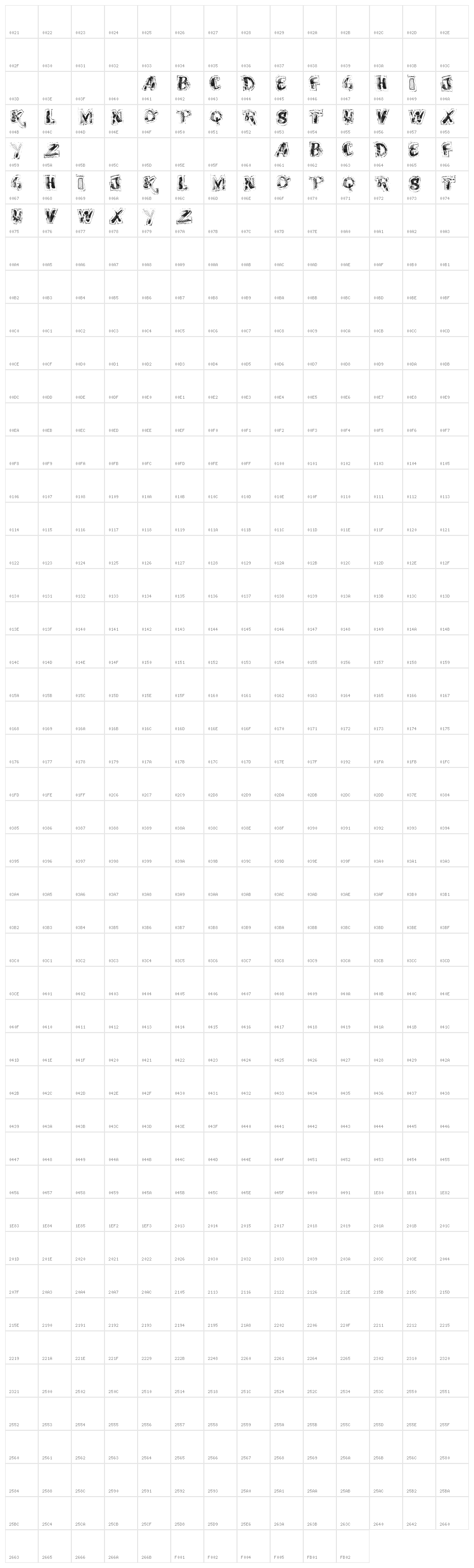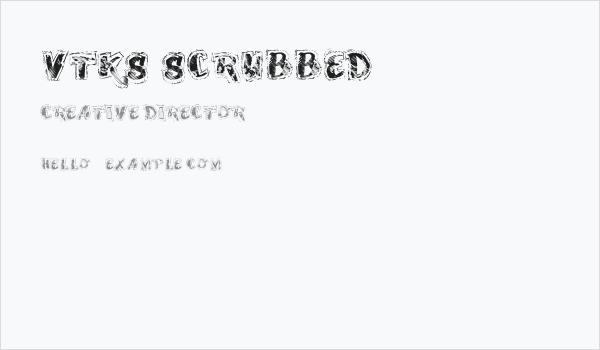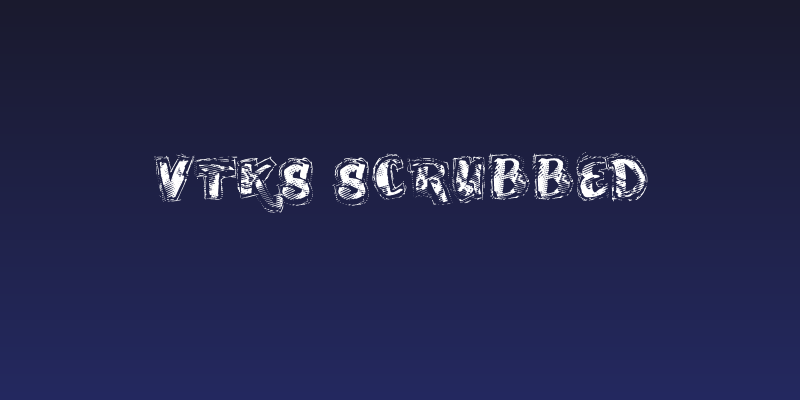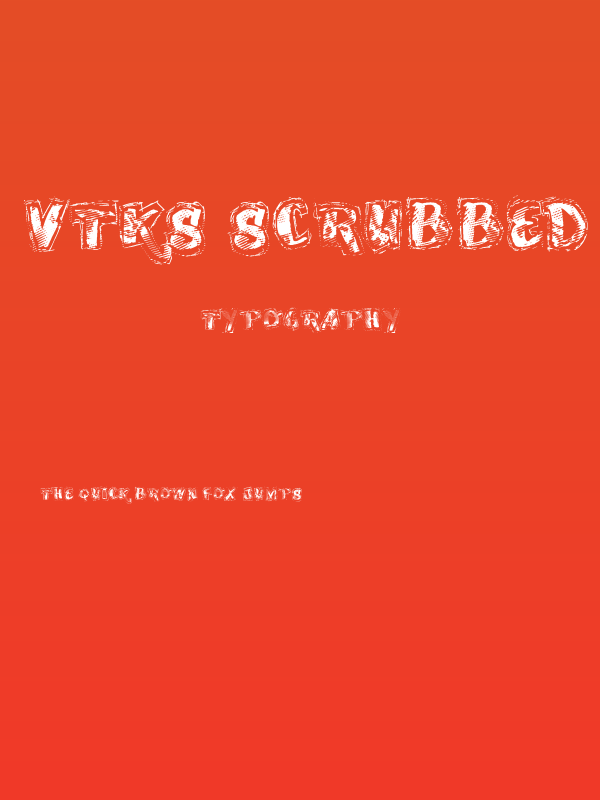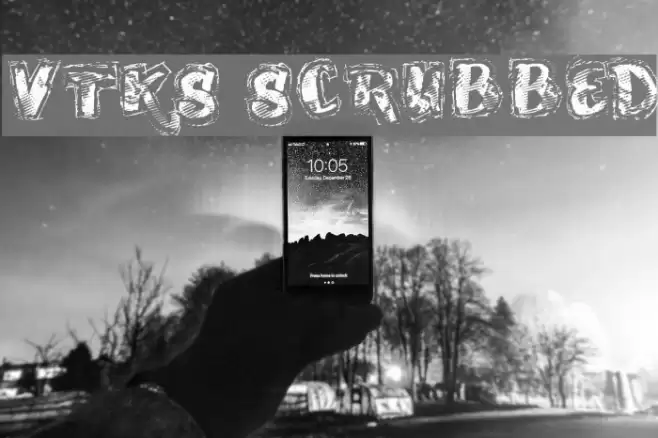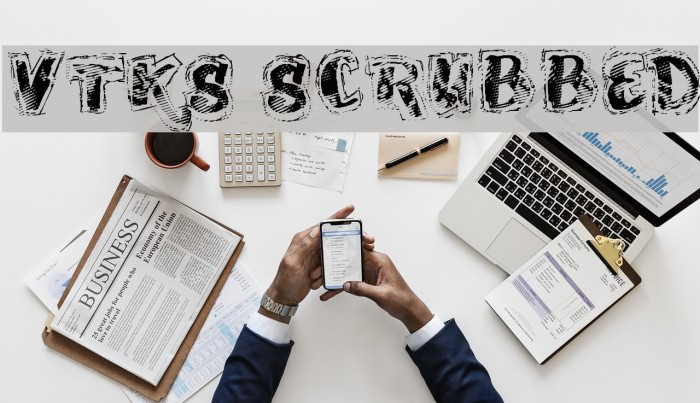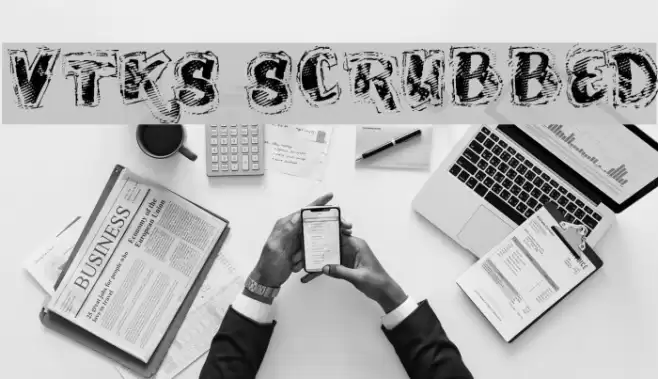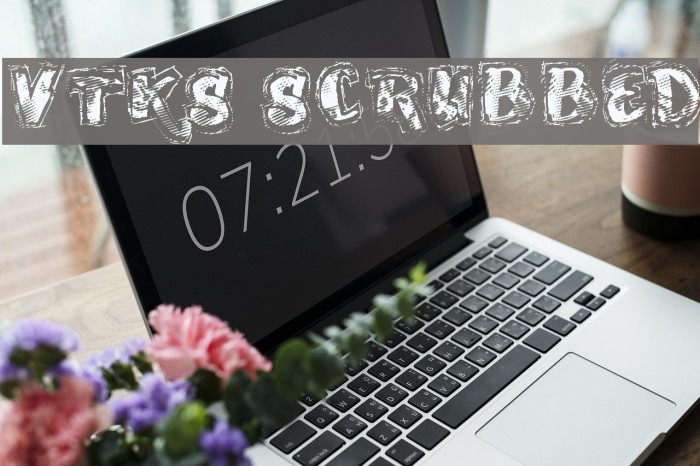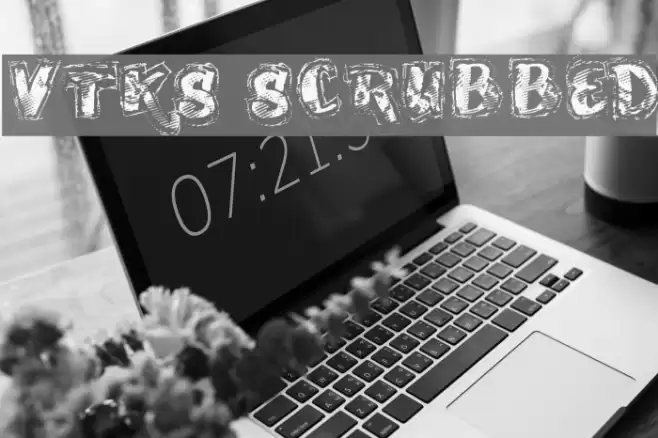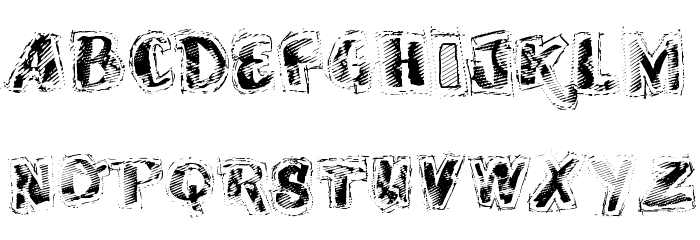
VTKS SCRUBBED Font
| Estilo general | Grunge, Artistic |
| Caso de uso | Logos, Posters, Album Covers |
| Proyectos propuestos | Perfect for album covers, posters, streetwear branding, and edgy graphic designs. |